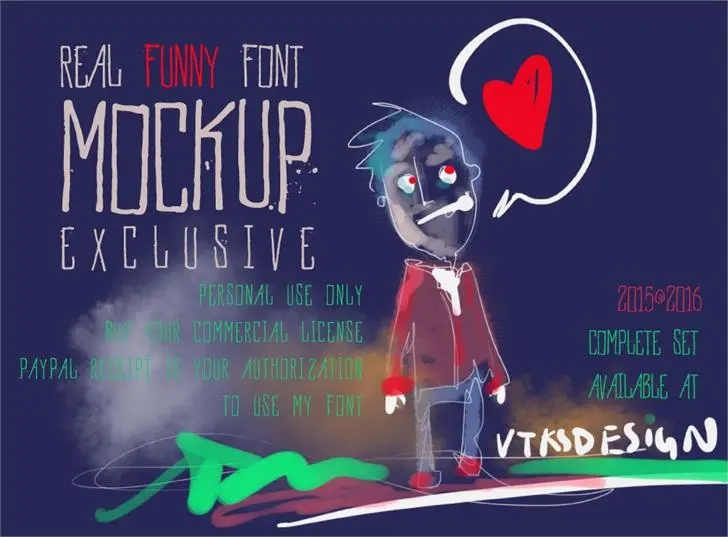
A fonte Vtks MockUp é perfeita para aplicativos de design impressão profissional que valorizam uma aparência minimalista e moderna. Com seu estilo display, esta fonte oferece um toque sofisticado a qualquer projeto gráfico ou site que exija elegância e força visual. Hamilton, o designer desta fonte, criou algo único e versátil que se destaca em seus projetos. Ideal para elementos de marca como logotipos, nomes de empresas e design web, Vtks MockUp oferece uma combinação perfeita de simplicidade e poder. Com uma aparência limpa e moderna, esta fonte se adapta a diversos estilos e usos do mercado gráfico atual. Se você está procurando por uma fonte que reflete elegância e confiabilidade em suas criações, Vtks MockUp é certamente o item perfeito para sua lista de recursos gráficos.